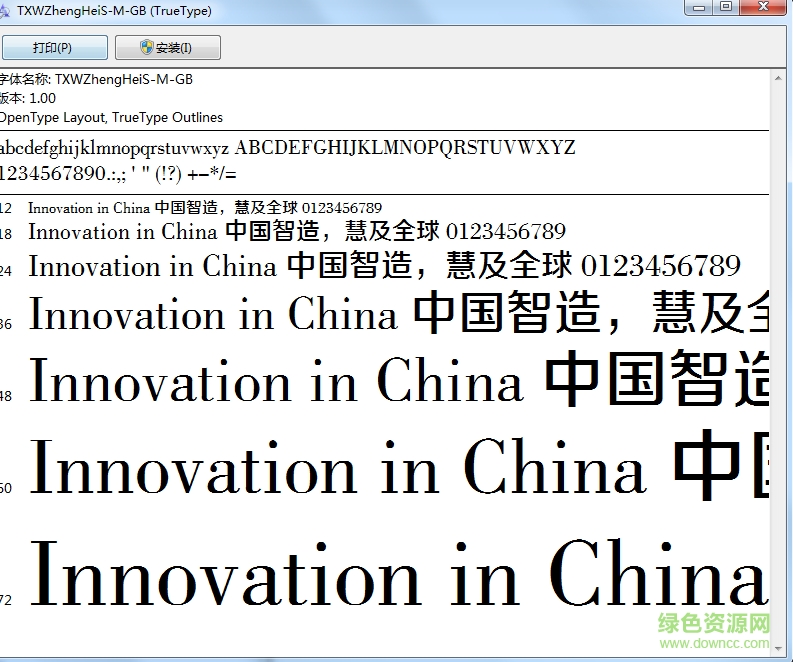
碳纖維正準(zhǔn)黑是一款中文簡(jiǎn)黑字體,端正嚴(yán)肅之風(fēng),容納藝術(shù)字體之底蘊(yùn),適合各種正規(guī)文字、名片設(shè)計(jì)等場(chǎng)合,歡迎大家來(lái)綠色資源網(wǎng)免費(fèi)使用!
碳纖維正準(zhǔn)黑作為碳纖維字體系列的簡(jiǎn)黑之作,延續(xù)了管用的端正嚴(yán)明之風(fēng),給整以大氣莊嚴(yán)之感。